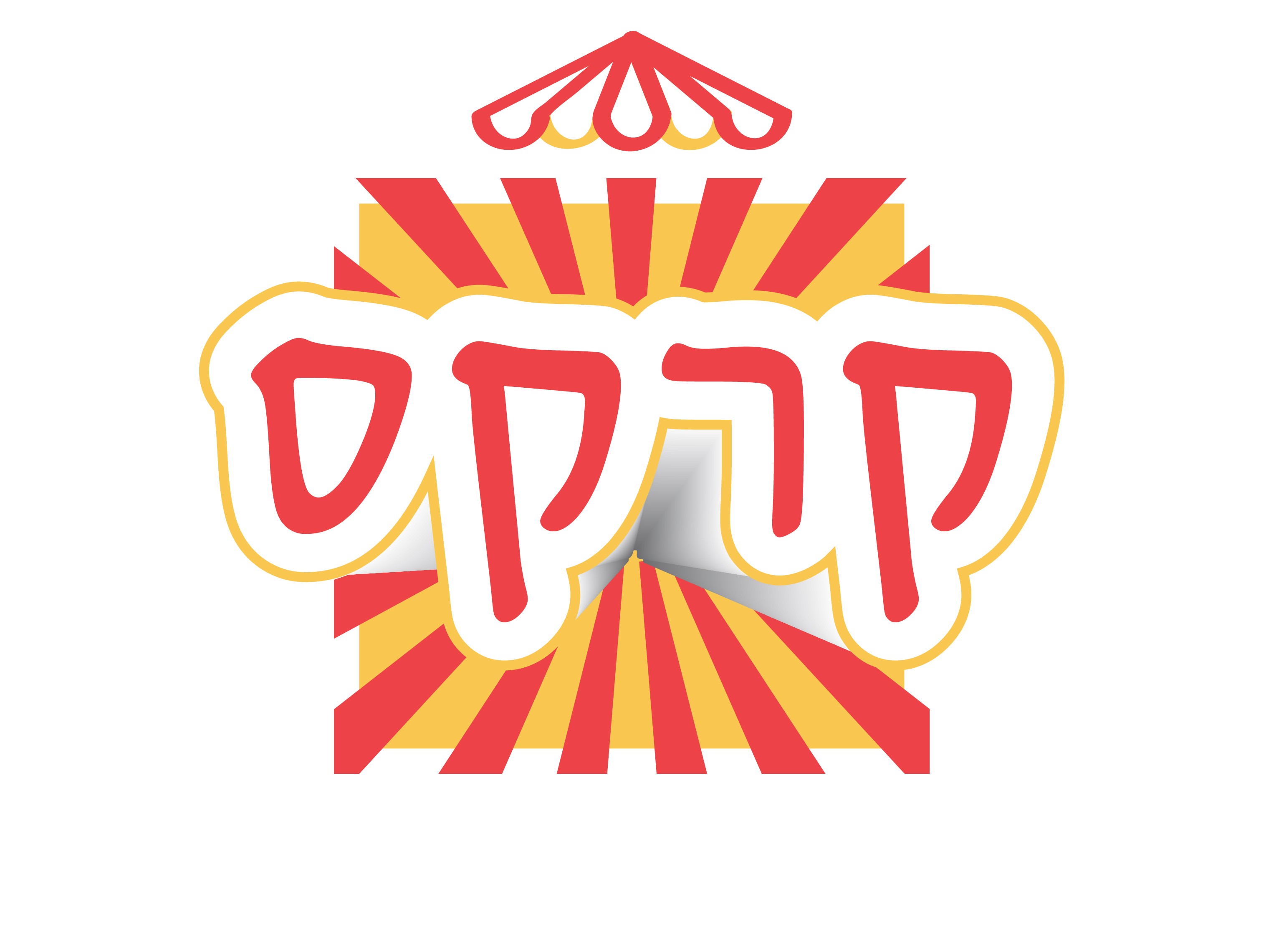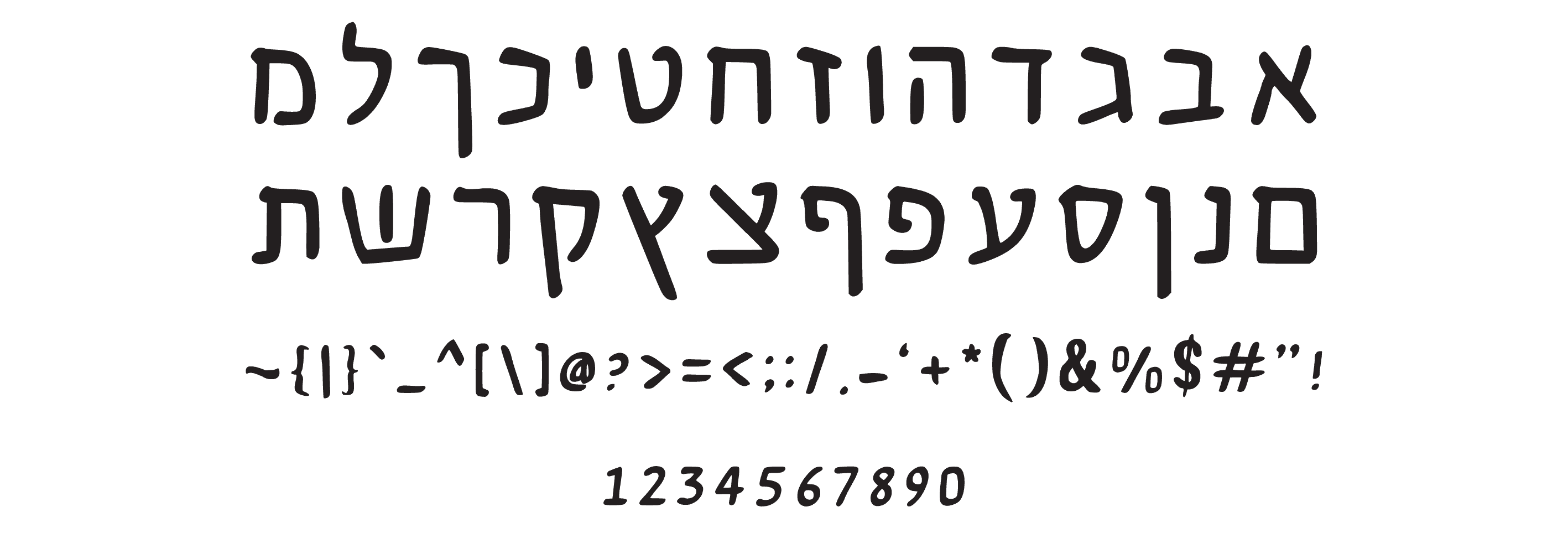
פונט קרקס
Manual Hebrew font, playful and festive, perfect for posters, performances, and colorful logos.
קרקס — פונט עם כניסה של כוכב
ברגע שהוא מופיע על המסך, אי אפשר להתעלם ממנו.
קרקס הוא פונט עברי שובב, תוסס ומלא שמחת חיים, עם מראה ידני שמזכיר שלטים מצוירים בירידים ובקרקסים.
האותיות בו עקומות בעדינות, כאילו נכתבו בטוש שמנמן, ויוצרות תחושת חופש, כיף ותנועה.
הוא מושלם לעיצובים שרוצים למשוך תשומת לב, להכניס חיוך, ולשדר אווירה של מופע, פסטיבל או חגיגה צבעונית.
איפה הוא מרגיש בבית?
🎪 פוסטרים לקרקסים, מופעים וירידים
🎉 עיצובי אירועים חגיגיים
🎨 לוגואים למותגים שמחים וקלילים
✏️ כותרות עם אנרגיה צעירה ומלהיבה
למי הוא מתאים?
למעצבים שמחפשים להוסיף לעיצובים שלהם תחושת חופש, תנועה ושמחה, וגם לכל מי שרוצה לשדר אווירה צבעונית ומלאת חיים.